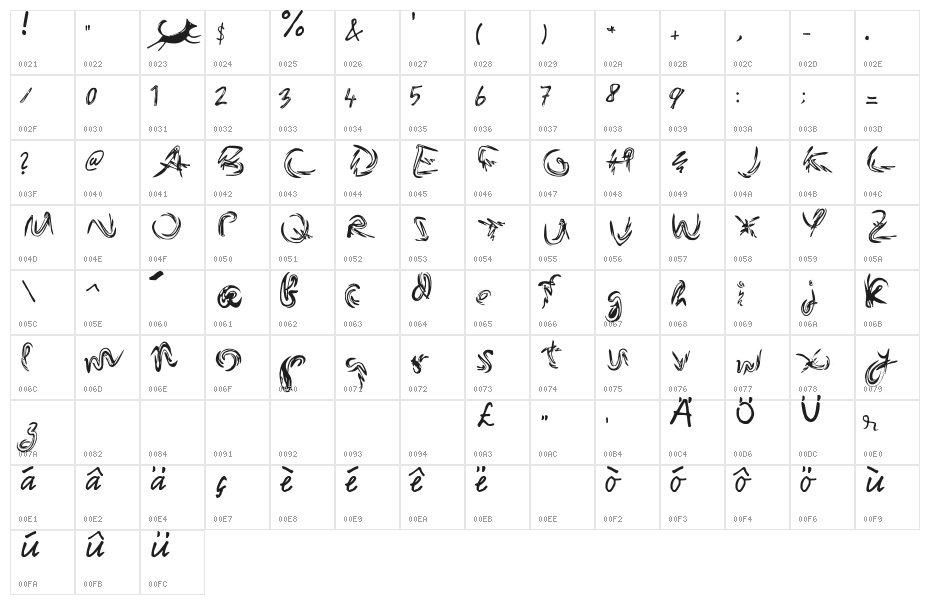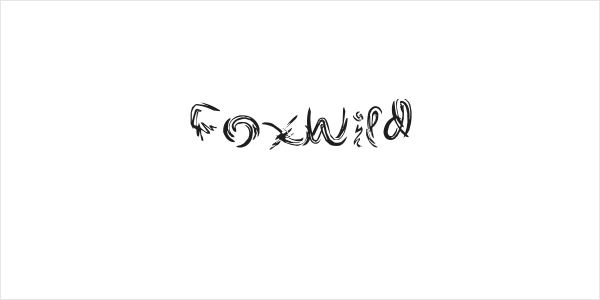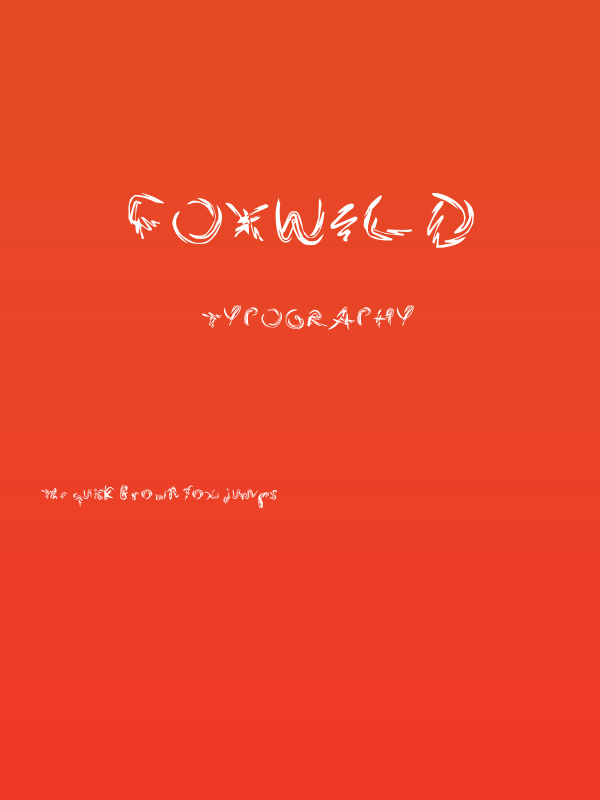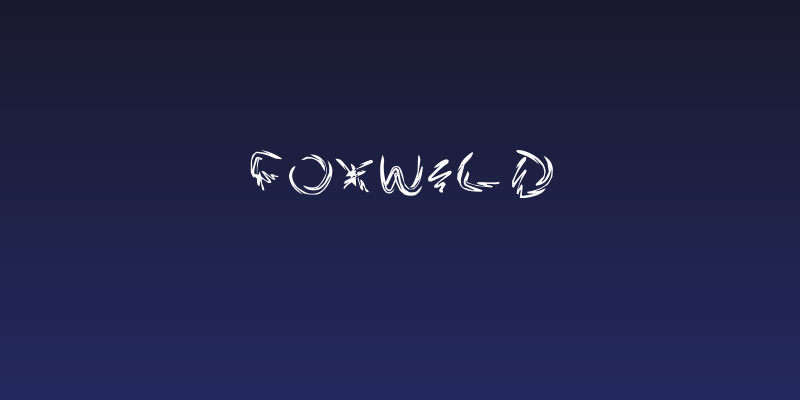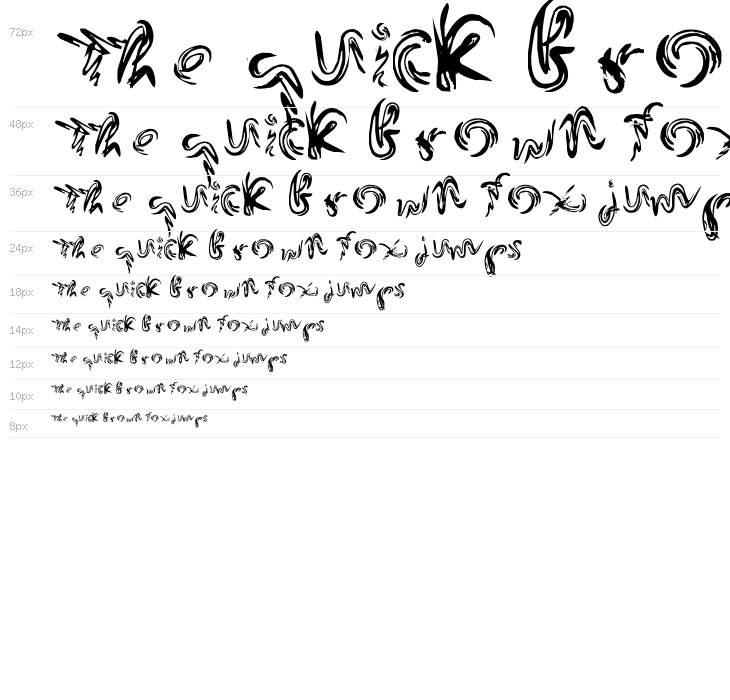
FoxWild Font
| مشاريع مقترحة | Ideal for projects that require a creative touch, such as album covers, posters, branding for artistic ventures, or any design that seeks to convey energy and movement. |